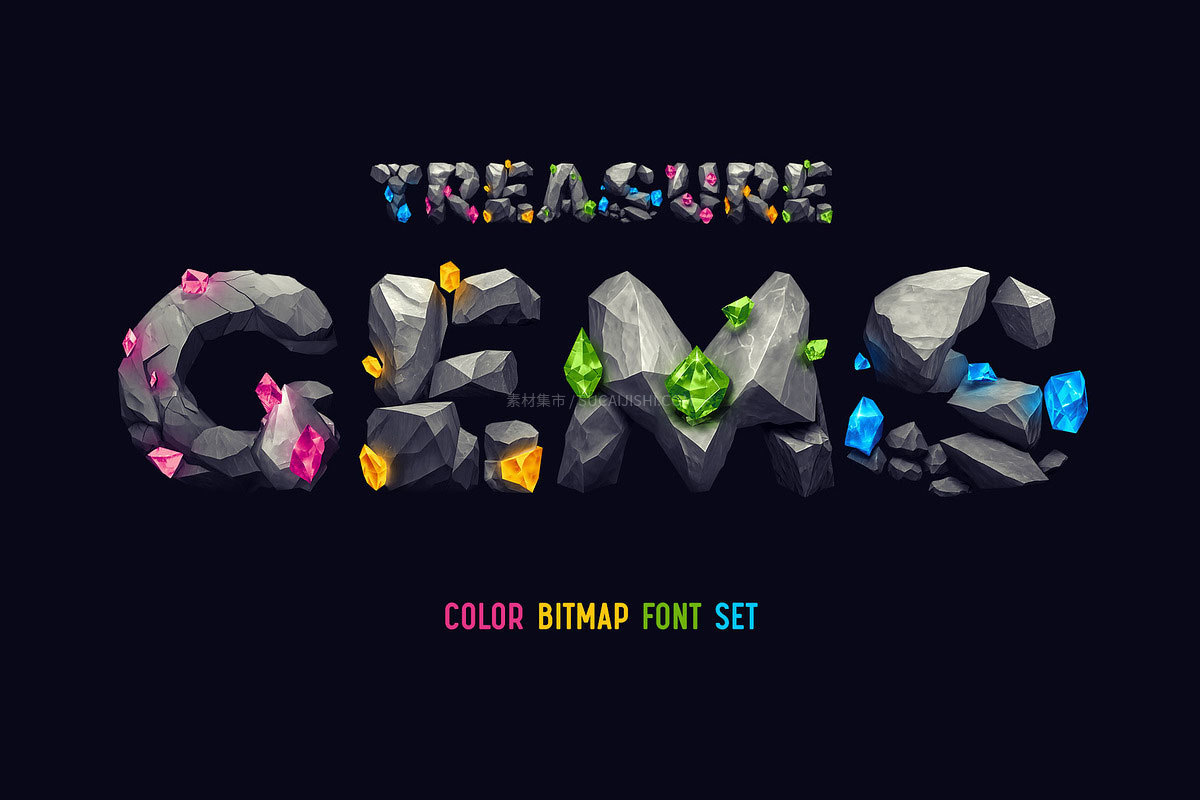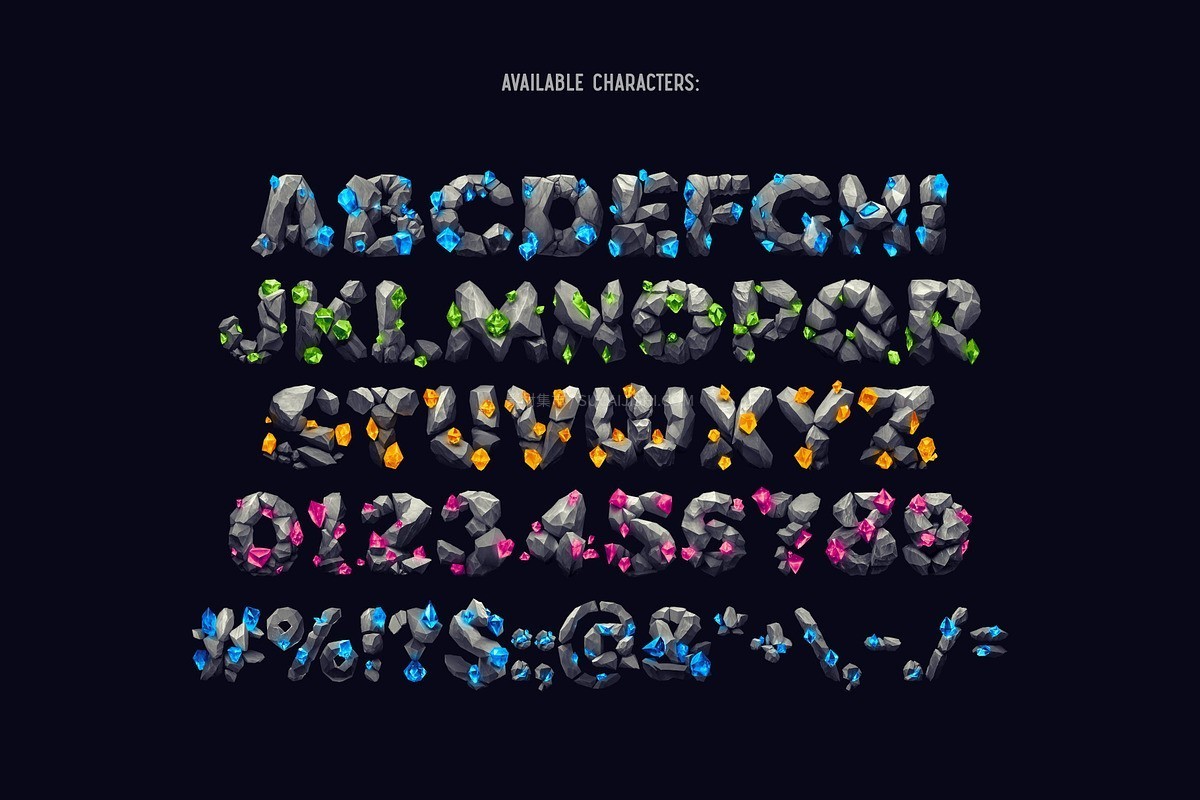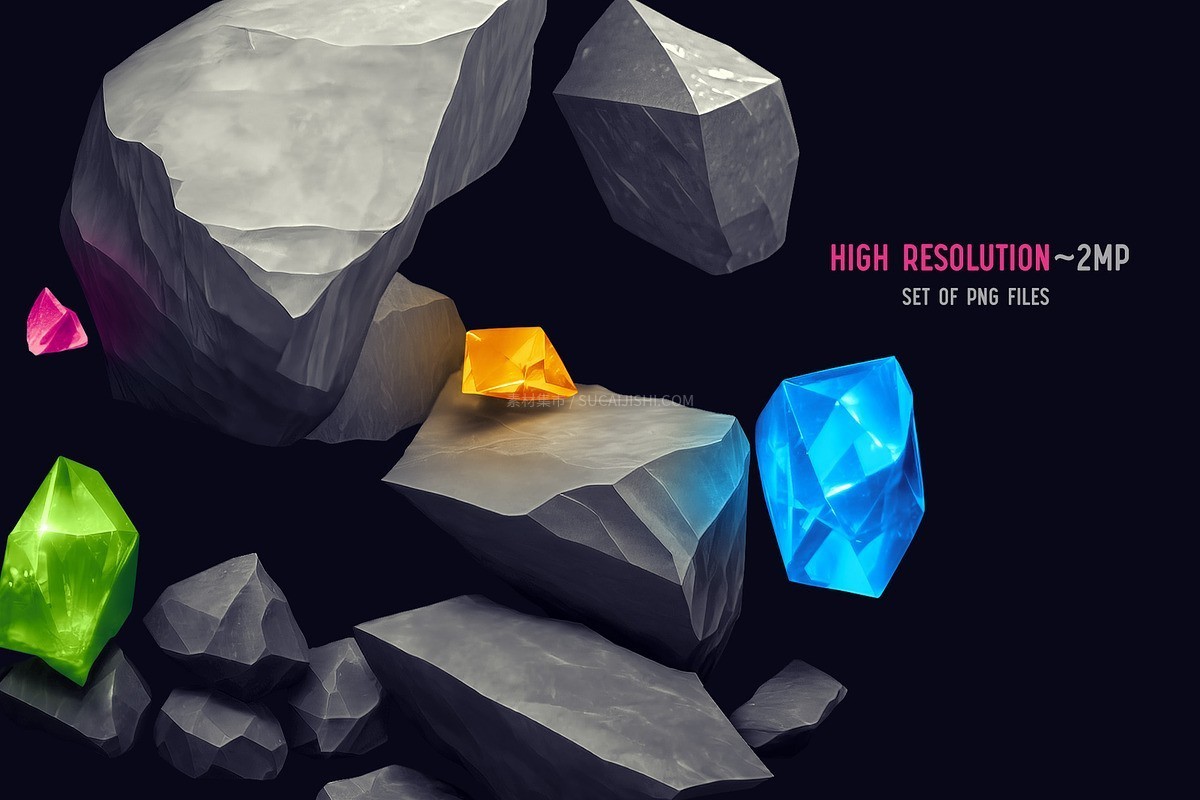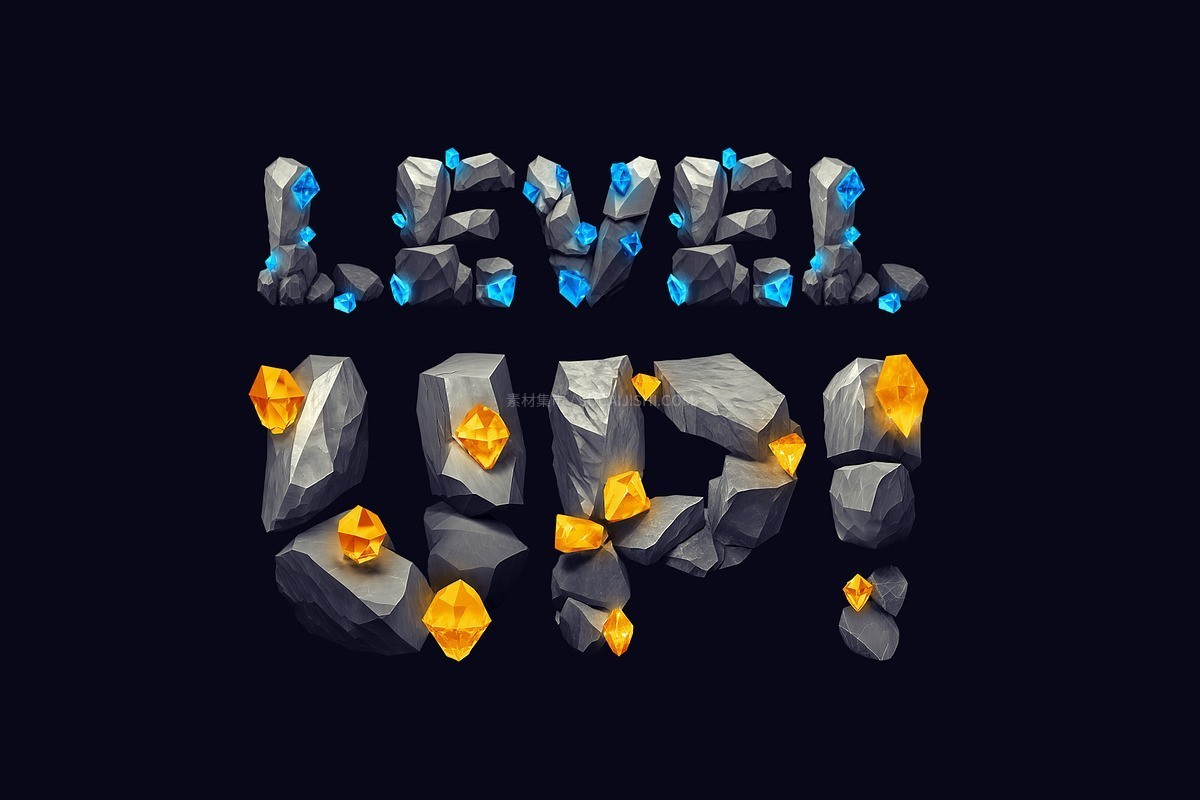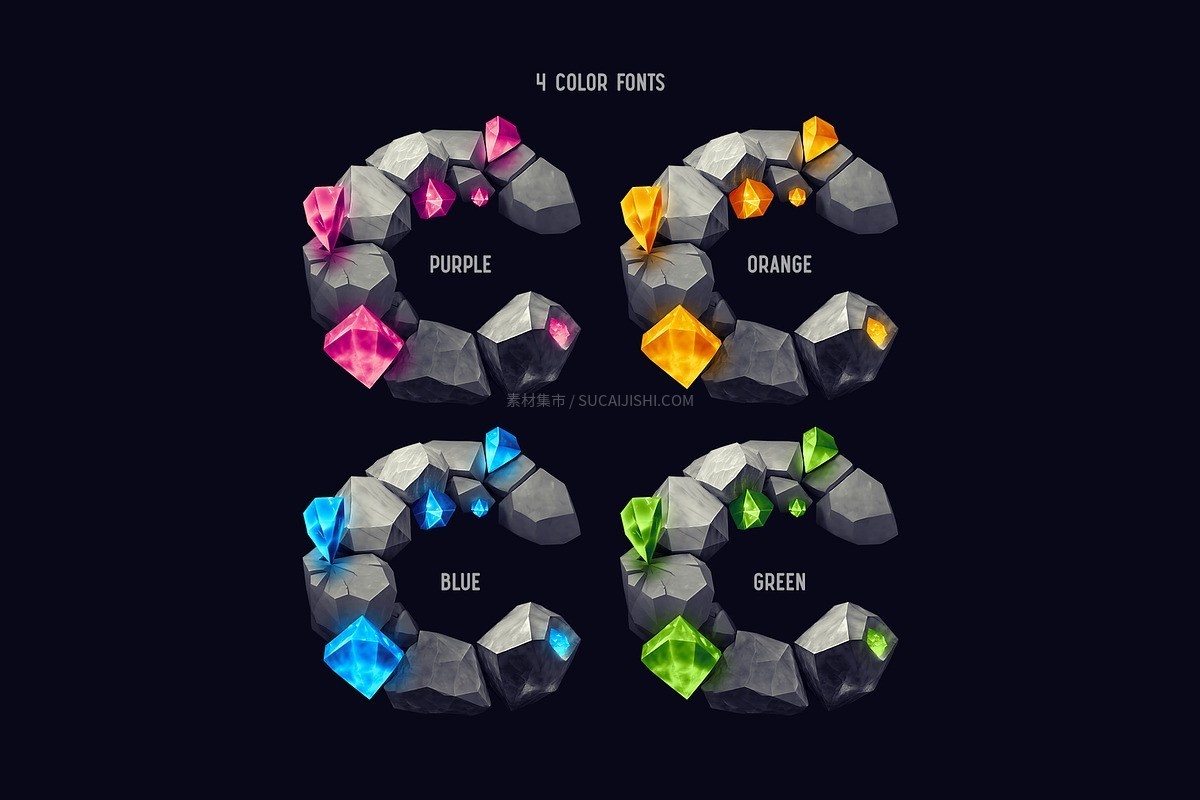
Treasure Gems魔法宝石3D位图字体
Treasure Gems 是一款充满奇幻色彩的 3D 艺术字体集。它将沉稳的灰色岩石与璀璨的闪耀宝石完美融合,提供 4 种不同色系的宝石版本(红、绿、蓝、紫等),瞬间为您的作品注入神秘的魔法气息。
Treasure Gems魔法宝石3D位图字体
本套件采用创新的 OpenType-SVG 技术,允许您像使用普通 OTF 字体一样直接输入带有颜色、质感和光效的文字。